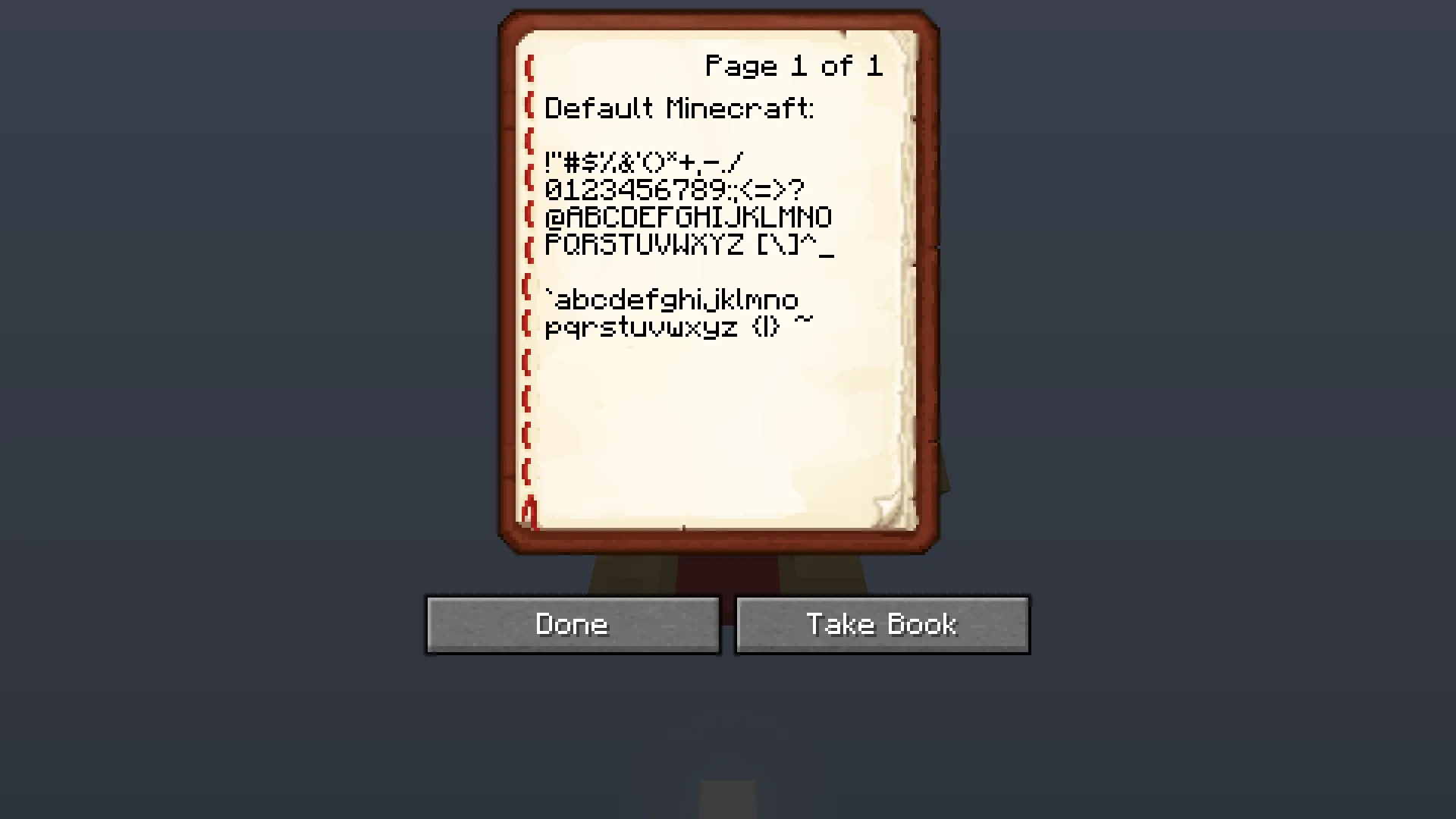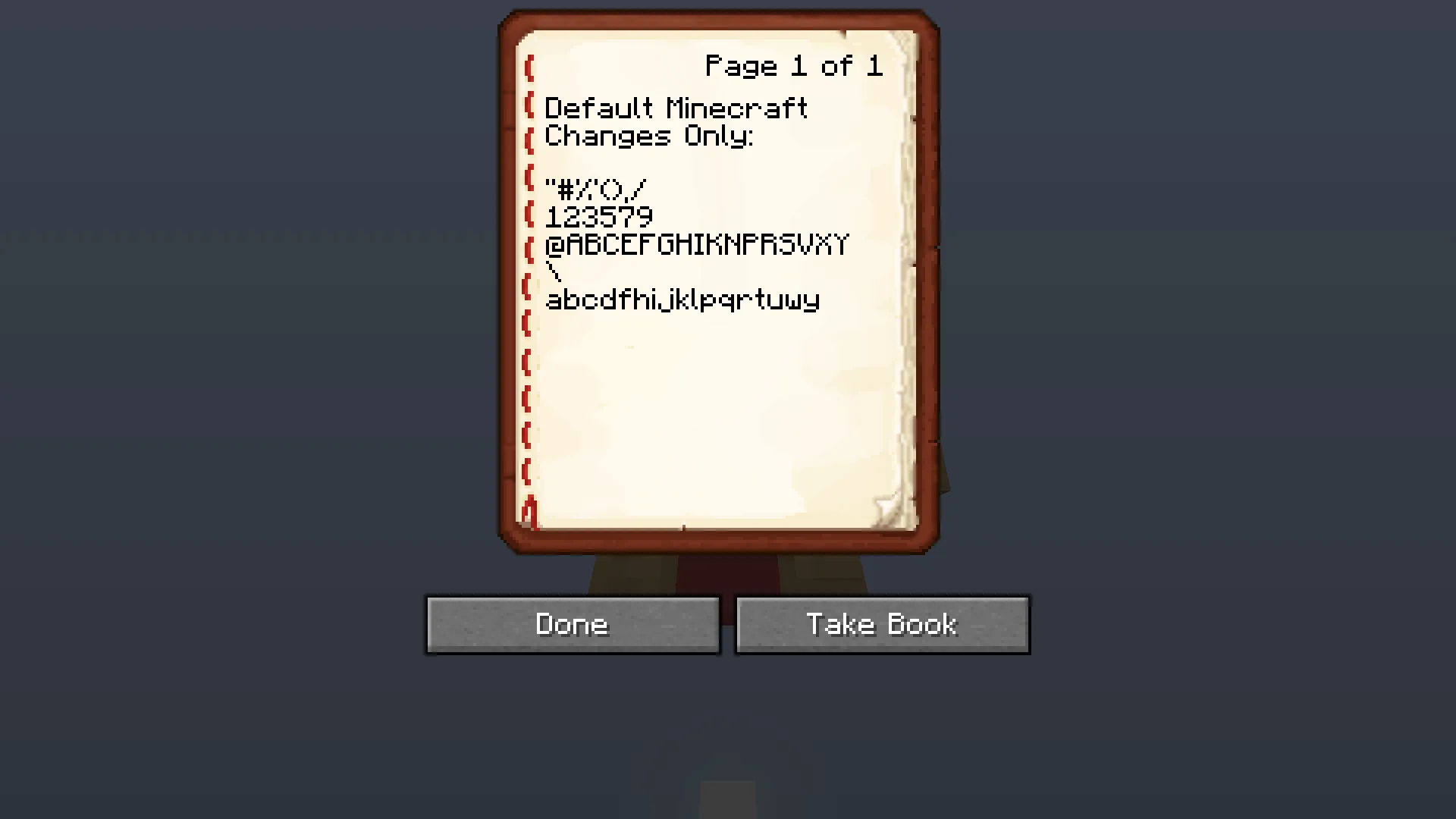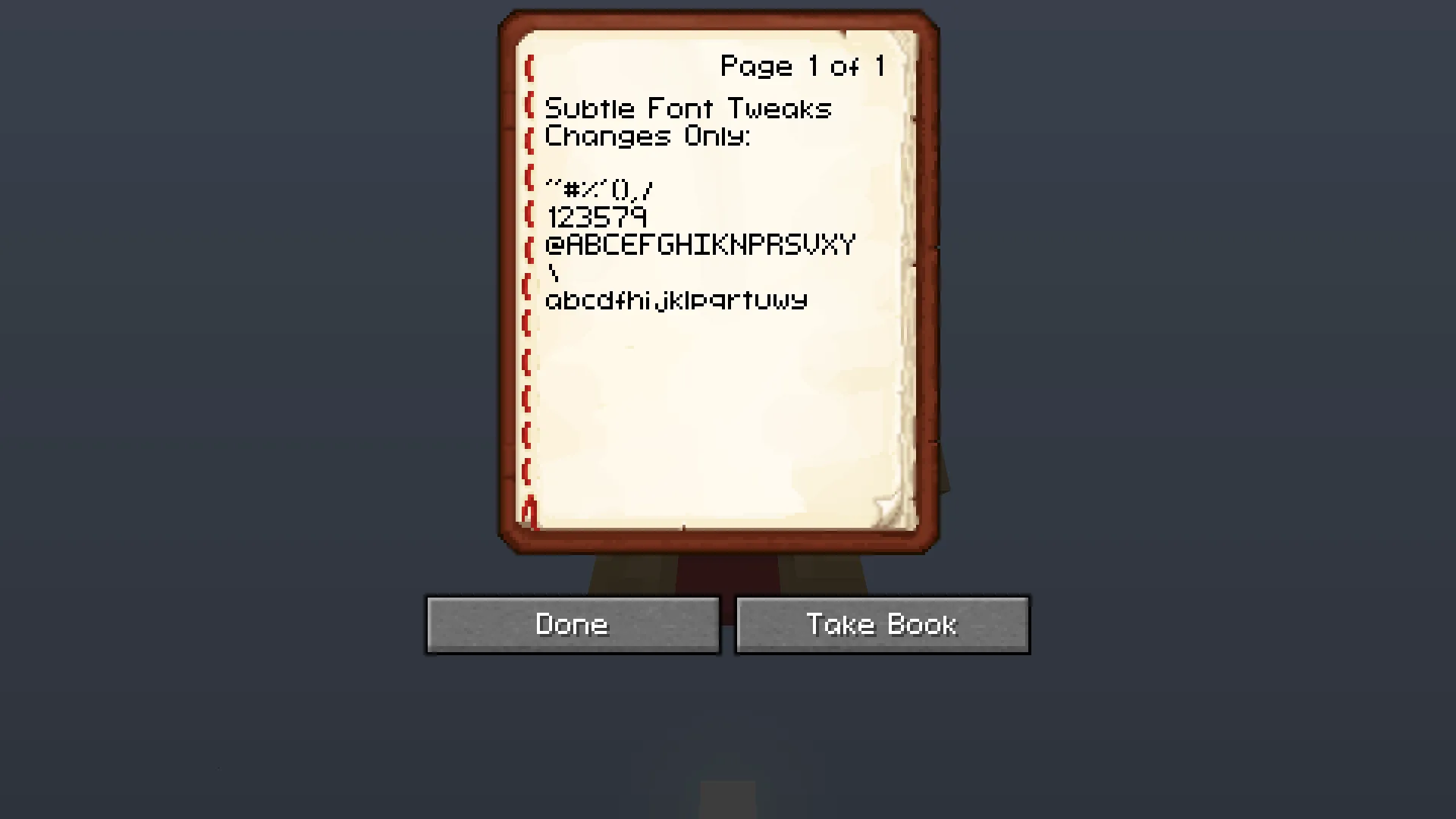
Subtle Font Tweaks
Этот шрифтовой пакет делает строчные буквы меньше и округлее, а заглавные — центрированными. Это тонкие изменения, придающие свежесть стандартному шрифту Minecraft.
Этот шрифтовой пакет вносит небольшие изменения в стандартный шрифт Minecraft, который мы все видели годами. Он делает строчные буквы меньше и округлее, а заглавные буквы центрирует, устраняя их смещение. Эти тонкие настройки придают шрифту свежий вид, сохраняя при этом ванильную атмосферу.
Пакет идеально подходит для тех, кто устал от стандартного шрифта, но не хочет радикальных изменений. Он предлагает незначительное обновление, которое улучшает читаемость и визуальную гармонию, оставаясь совместимым с основным стилем игры.